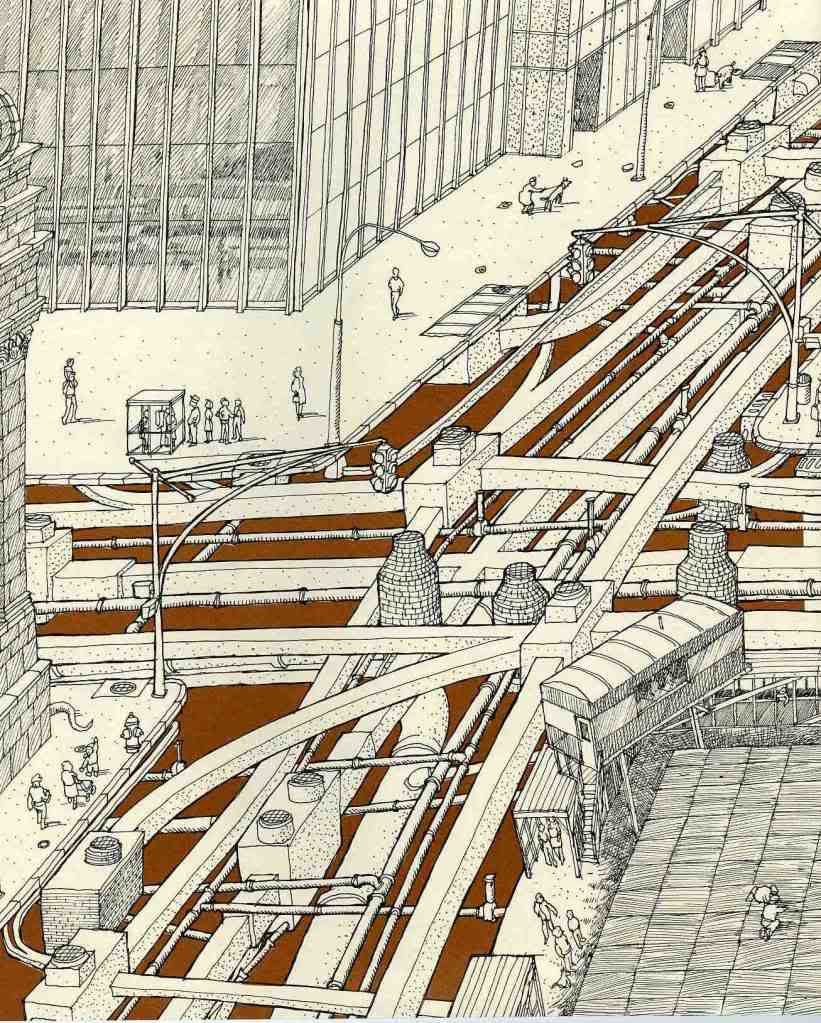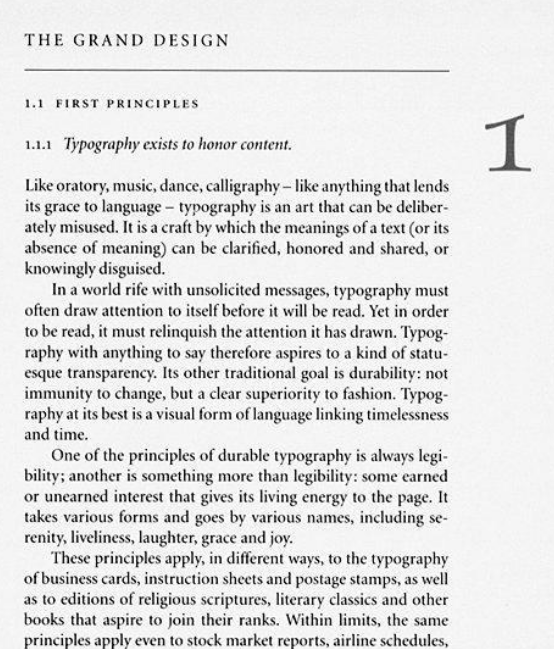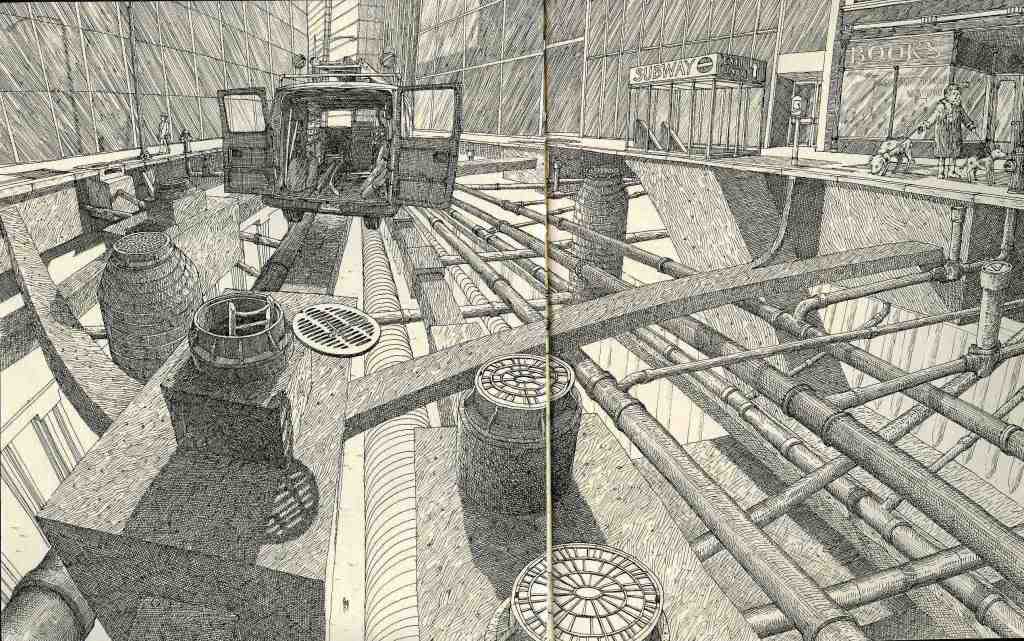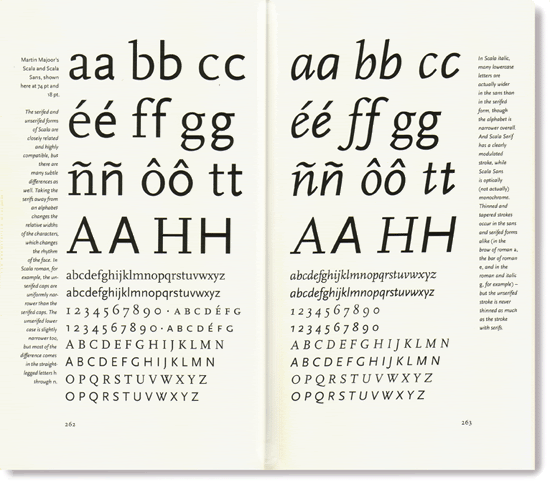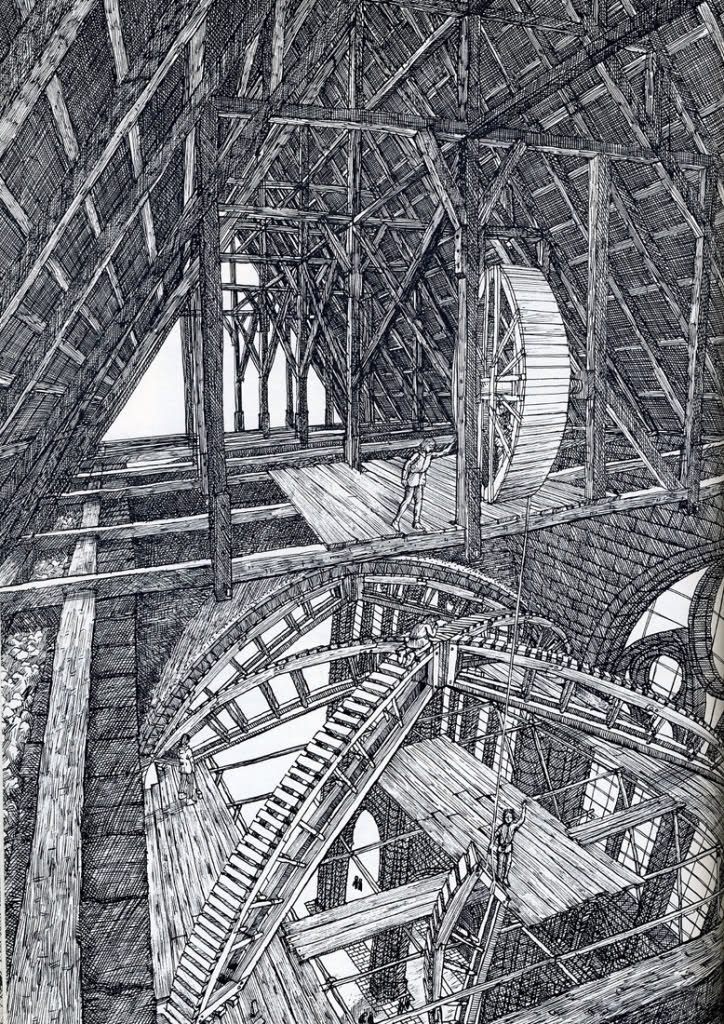
Vorbildliche Lehrbücher
wir haben den Auftrag bekommen ein Lehrbuch aus einem technischen Bereich zu gestalten. Da wollen wir natürlich die neuesten Erkenntnisse in gestalterischer Hinsicht einfließen lassen.
Erste Frage:
Welche Lehrbücher (bevorzugt aus dem technischen/naturwissenschaftlichen Bereich) haben euch im Laufe eurer Gestaltungsauseinandersetzung besonders gefallen? Und warum?
Zweite Frage:
Kennt wer ein Buch, das sich mit Gestaltungsfragen im Lehrbereich auseinandersetzt?
was meinst du genau mit gestaltung? das, was in den bereich der typographie fällt, oder das, was in den bereich didaktik (und/oder medienrezeption und/oder lernpsychologie) fällt?
auch wenn es am bedarf wohl meilenweit vorbei geht: http://www.mediendidaktik.org/tag/lehrbuch-der-zukunft/
oh, und falls ihr multimediale elemente einbaut, achtet auf plattformunabhängigkeit. total geil, wenn schüler nur aufgrund eines mangelnden betriebsystem ne sechs wegen nicht gemachter hausaufgaben bekommen.
was meinst du genau mit gestaltung? das, was in den bereich der typographie fällt, oder das, was in den bereich didaktik (und/oder medienrezeption und/oder lernpsychologie) fällt?
Hmm, eigentlich eine Mischung aus beidem. Ich würde mich gerne schlau machen, wie man ein (für mich) trockenes Thema didaktisch anspruchsvoll und formal spannend aufbereiten kann.
der trend der didaktik geht hin zu bunt um jeden preis, verschiedene stile um verschiedene wichtigkeiten zu verdeutlichen und überhaupt. kann leider nur von vielen missgriffen aus dem bereich klassische philologie berichten, in dem hervorragende lehrbücher auf krampf modernisiert wurden, wobei die lehr/lernerfolge hinter bunt/verspielt zurücktraten.
schau dir am besten lehrbücher verschiedener generationen an, jenseits von bildungsmessen und unverschämt teuren verlagsshops hat dein bundesland ein institut für lehrerfortbildung (kann auch anders heißen). dort gibt es eine lehrbuchsammlung. universitäten (sowohl die unibibliotheken als auch die fb-bibliotheken) sind eher schwach bestückt und zudem sind die exemplare auf dem ganzen campus verteilt.
dann gilt es auch noch die anforderungen der länder zu erfüllen (die schulbehörden haben so einen anforderungskatalog, nach dem ein buch überhaupt für den unterricht zugelassen wird). siehe auch http://www.bildungsserver.de/zeigen.html?seite=522
dabei fällt mir noch ein, wenn du ausreichend zeit hast, frag einige lehrer direkt, was sie gut/schlecht finden. und dann einige mediendidaktiker und lernpsychologen. bei schülern hast du schnell antworten wie "comic sans" und 14punkt (selbst in latein erlebt, habt ihr schon mal cicero in comic sans gelesen? pfui bäh).
und vergiss nicht, dass lehrer -- warum auch immer -- nur arial, times new roman und comic sans kennen. und etwas zu fetten, doppelt zu unterstreichen und dann kursiv zu stellen ist hübsch. wirklich.
Danke für dein Engagement, Phoibos. Den Weg der Pädagogen gehe ich parallel. Mein Ansatz hier zu posten war, auch aus der Gestaltungsnische her, interessante Ideen zu bekommen. Direkte Frage: Hast du ein konkretes Beispiel eines vorbildlichen Lehrbuches parat? Aus welchem Fach auch immer …
von den vielen lehrbüchern im bereich altgriechisch/latein gefällt mir als lehrbuch am besten:
die roma-reihe vom buchners-verlag beispielhaft: http://www.amazon.de/gp/product/3766155717
die sind, zumindest in den mir vorliegenden exemplaren äußerst unbunt. haben doch einen guten mix aus übungen, texten und infotexten.
von den grammatiken gefällt mir ob übersichtlichkeit und typographie (gut, es gibt ein, zwei glitches) sehr gut folgendes:
http://www.amazon.de/Lateinische-Grammatik-Neubearbeitung-Grundlage-Landgraf-Leitschuh/dp/3637873729/ref=pd_sim_b_2
und, deutlich weniger (aber das inhaltlich):
http://www.amazon.de/Hellas-Grammatik-Griechischen-Friedrich-Maier/dp/376615821X/ref=sr_1_1?ie=UTF8&qid=1305038729&sr=1-1
alptraumhafte grammatiken:
http://www.amazon.de/Grammateion-gefasst-Griechische-Lerngrammatik-kurzgefasst/dp/3126701701/ref=sr_1_1?s=books&ie=UTF8&qid=1305038807&sr=1-1 (auch inhaltlich etwas für den scheiterhaufen)
http://www.amazon.de/Kurzgefasste-Griechische-Schulgrammatik-Adolf-Kaegi/dp/3615701003/ref=sr_1_1?ie=UTF8&qid=1305038802&sr=1-1 (einzige, unübersichtliche bleiwüste)
dennoch auch hier ein wort zur warnung: zumeist empfindet man das lehrbuch, das man selbst erlitt, als das beste (siehe oben, roma und die lateingrammatik).
was ich in den didaktiken (geschichte und klassische philologie) aus den fehlern anderer gelernt habe, ist folgendes:
Gute Beispiele für überaus anschauliche Bilder geben die Werke von David Macaulay ab:
Wenn ich dich richtig verstanden habe, bist du auf der Suche nach ein wenig Inspiration. Vielleicht findest du hier etwas: http://www.stiftung-buchkunst.de/